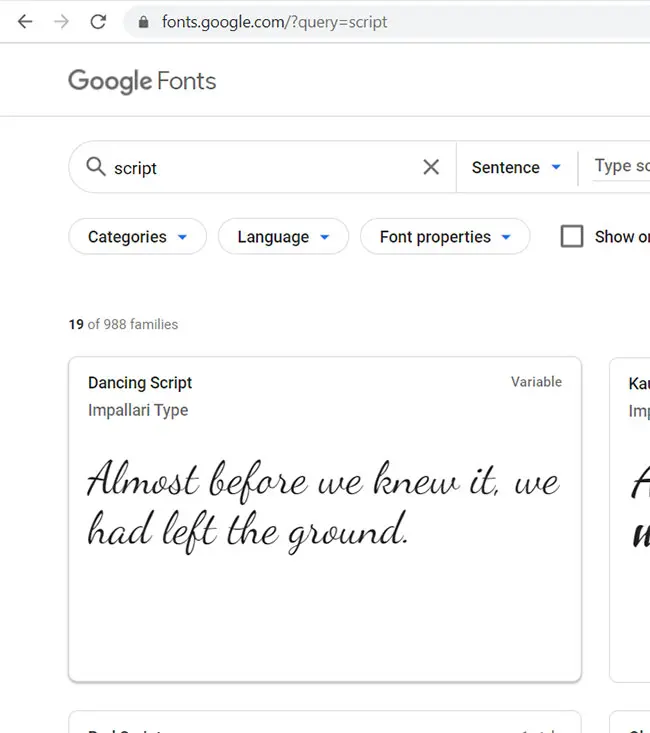
Die beste kursive Schriftart für Microsoft Word hängt von den persönlichen Vorlieben ab. Daher ist es schwierig, eine bestimmte Schriftart als die „beste“ zu betrachten.
Einige kursive Microsoft Word-Schriftarten sind standardmäßig verfügbar, Sie haben jedoch auch die Möglichkeit, Ihre eigenen Schriftarten zu installieren.
Einige standardmäßige kursive Microsoft Word-Schriftarten
Wie bereits erwähnt, gibt es eine Handvoll kursiver Schriftarten, auf die Sie Zugriff haben, bevor Sie sich auf die Suche nach einer eigenen machen.
Einige Beispiele für die besten kursiven Schriftarten in Word sind:
- Segoe-Skript
- Lucida-Handschrift
- Edwardianische Schrift
- Kunstler Script
Unten sehen Sie ein Bild mit jeder dieser kursiven Schriftarten.
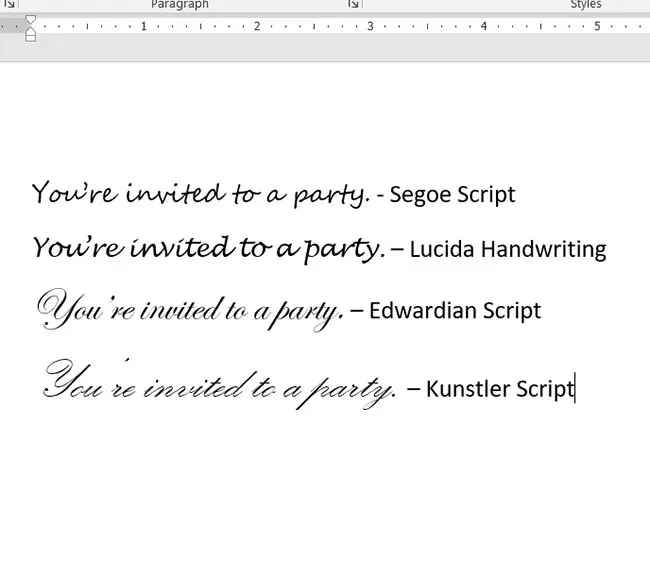
Welche davon die beste Signaturschrift in Word ist, hängt von der persönlichen Meinung ab. Beispielsweise könnte ich die Option „Edwardianische Schrift“ wählen, wenn ich in einem meiner Dokumente eine Schriftart für die Signatur in Kursivschrift benötige, andere bevorzugen jedoch möglicherweise stattdessen den Schriftstil „Künstler“.
Häufig gestellte Fragen zum Erhalten kursiver Schriftstile in Word
Wo finde ich eine gute, ausgefallene Schriftart in Word?
Je nachdem, wie Sie den Text mit der ausgefallenen Schriftart verwenden möchten, kann es auf diese Frage viele Antworten geben.
In unserem obigen Artikel haben wir einige der kursiven Schriftarten besprochen, die Sie von Google Fonts erhalten können. Diese kostenlosen Schriftarten sind eine gute Wahl für Dinge wie Einladungen, Zitate oder andere Arten von Dokumenten, bei denen eine Standardschrift möglicherweise nicht das gewünschte Erscheinungsbild erzeugt.
- Freestyle-Skript
- Französische Schrift MT
- Mistral
- Palace Script MT
- Wut kursiv
- Skript MT Bold
- Vladimir-Skript
Beispiele für diese Schriftarten sind im Bild unten dargestellt.